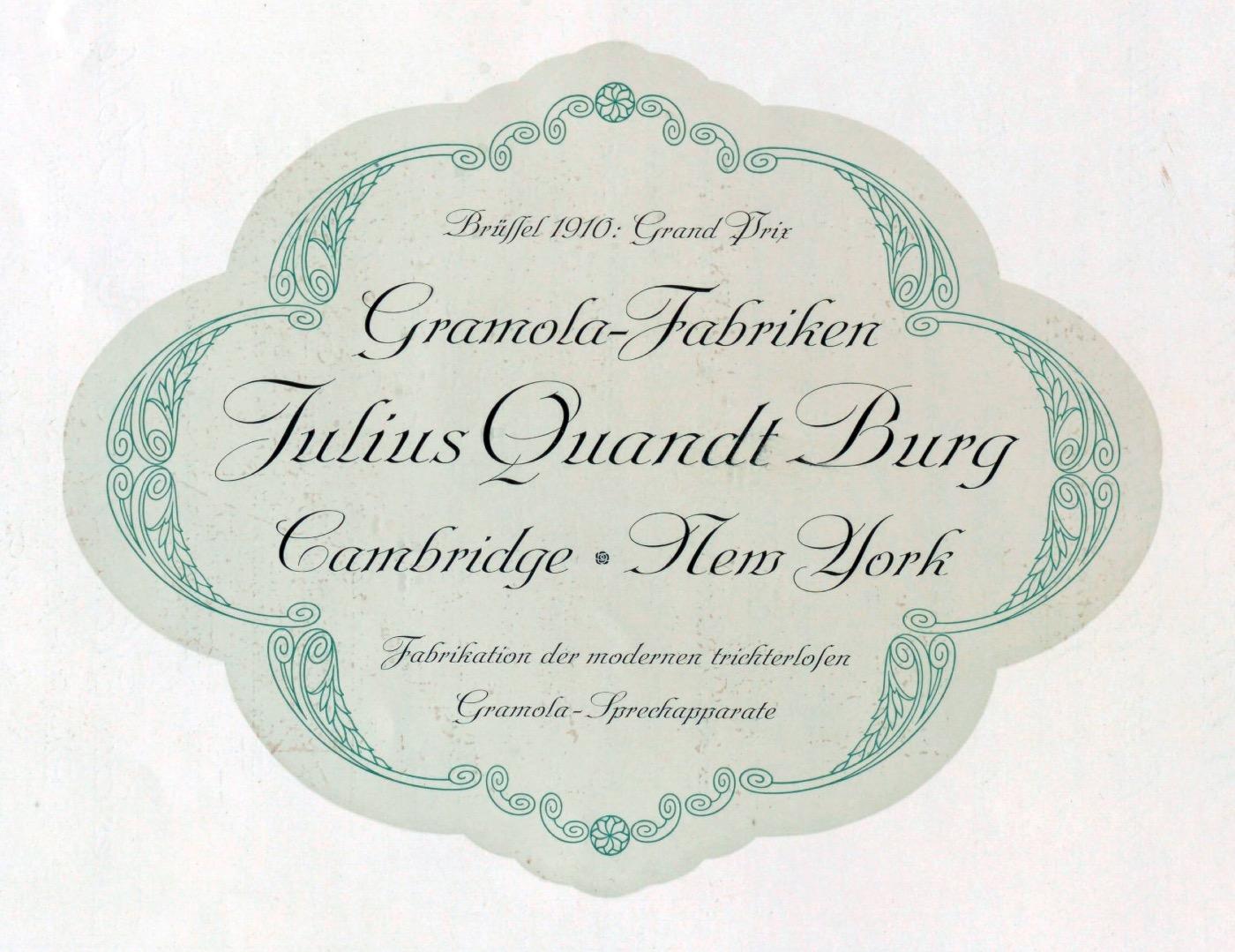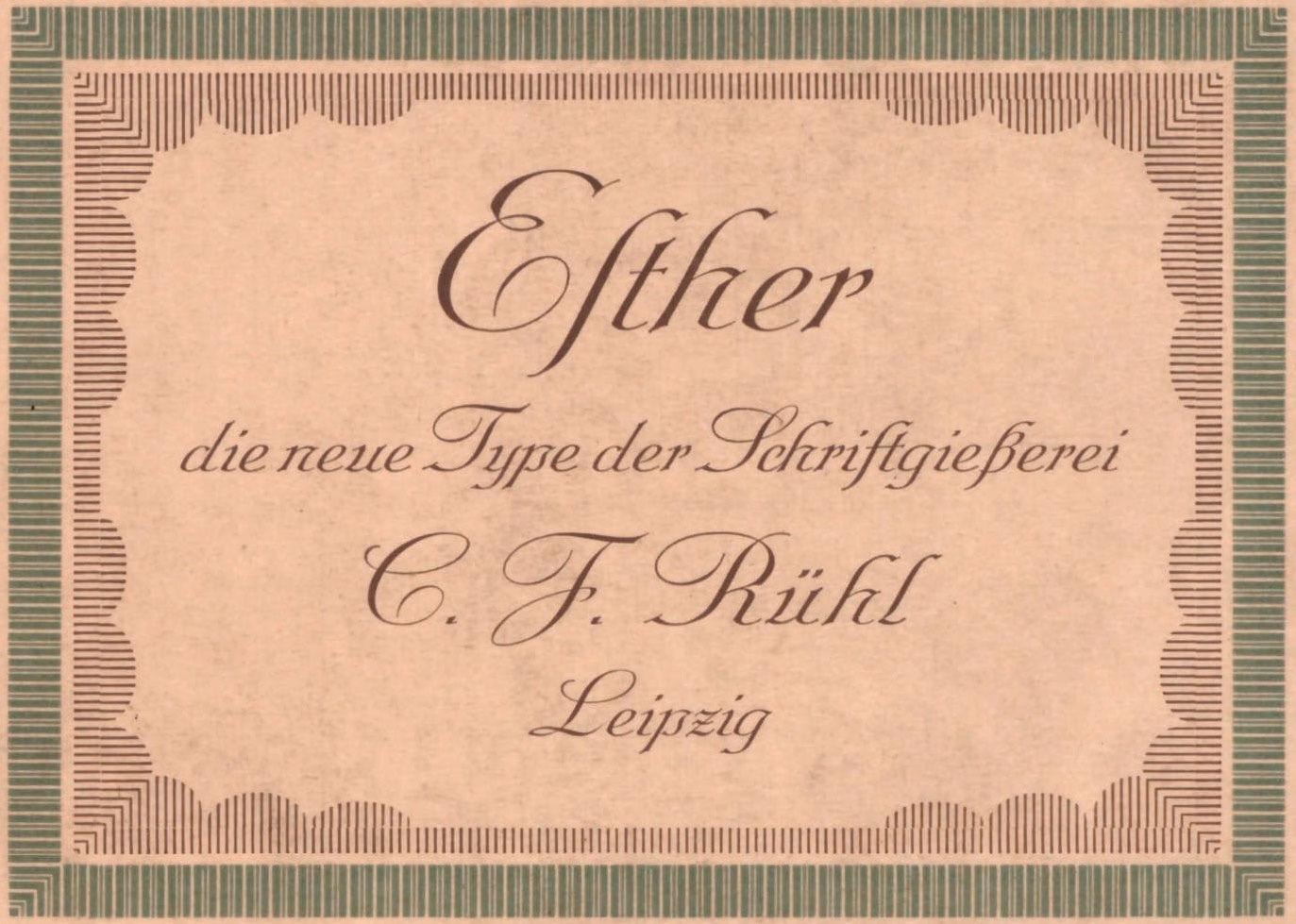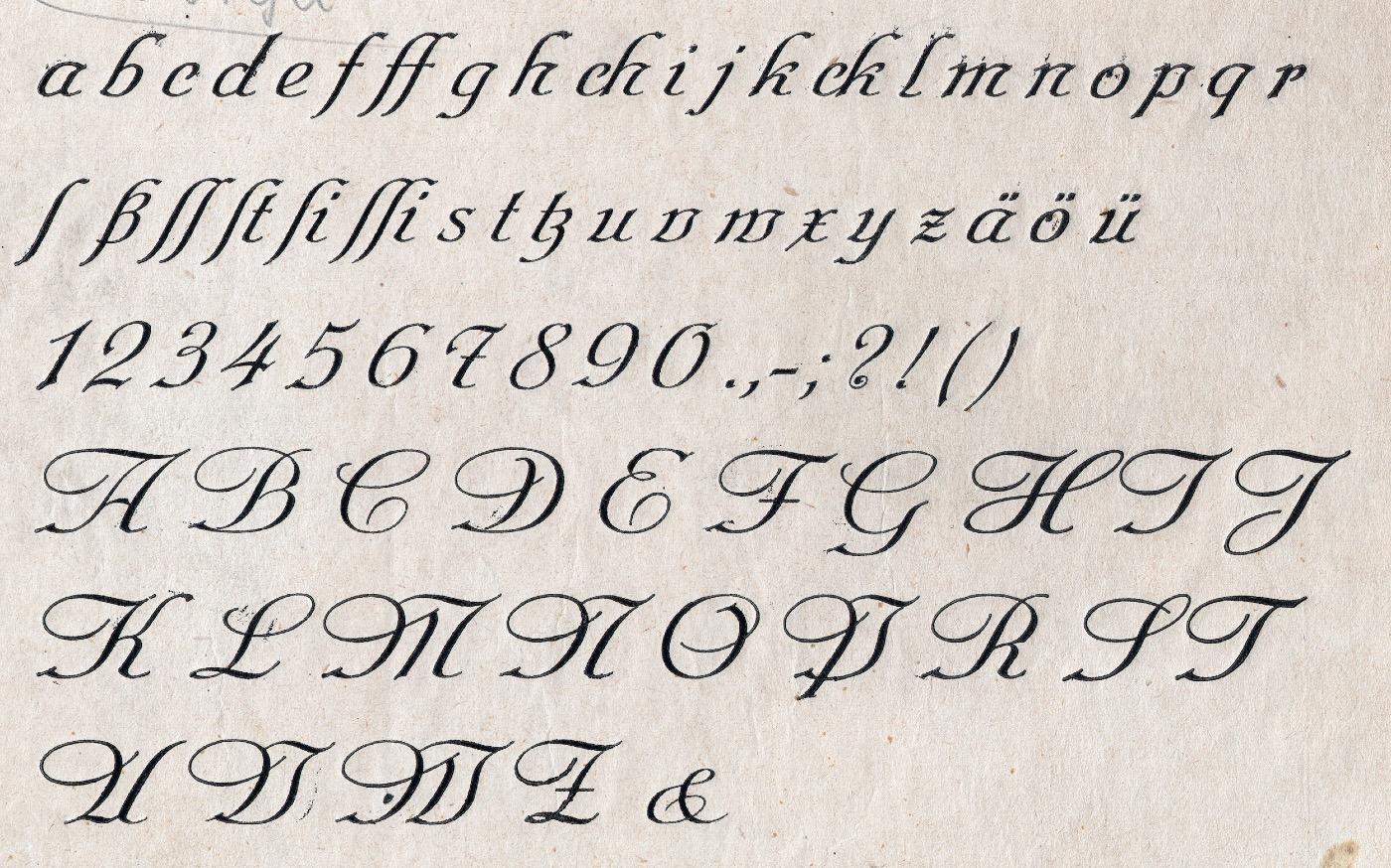
- 1913
- Antiqua Schreibschrift
Die Esther ist eine unverbundene Schreibschrift und erschien 1913 bei der Gießerei C.F. Rühl in Leipzig. Aus dem zugehörigen Schriftmusterheft: »Ständig bemüht, dem Buchdrucker mit künstlerischen, den Bedürfnissen der Praxis angepaßten Neuheiten aufzuwarten, habe ich in meiner vorliegend bemusterten ›Esther‹ eine Type geschaffen, die in der flotten kalligraphischen Schönheit der Einzelformen, wie in der eleganten vornehmen Gesamtwirkung den reinen Schreibschriften nicht nur nichts nachsteht, sondern sie bedeutend übertrifft, welcher aber durch Vermeidung der diffizilen Anschlüsse eine weit größere Verwendbarkeit und Lebensdauer gesichert ist. Nicht nur als Karten- und Zirkularschrift, sondern auch für aparte wirkungsvolle Reklame-Drucksachen u. dergl. ist sie vorzüglich geeignet …«.
Später wurde die Schrift bei Berthold weitergeführt. Digitalisierungen sind nicht bekannt.